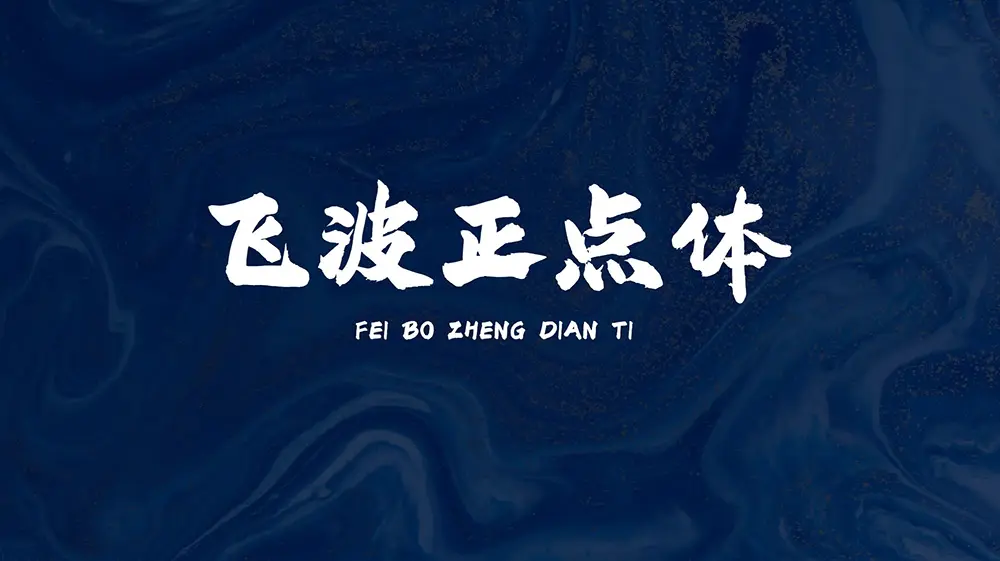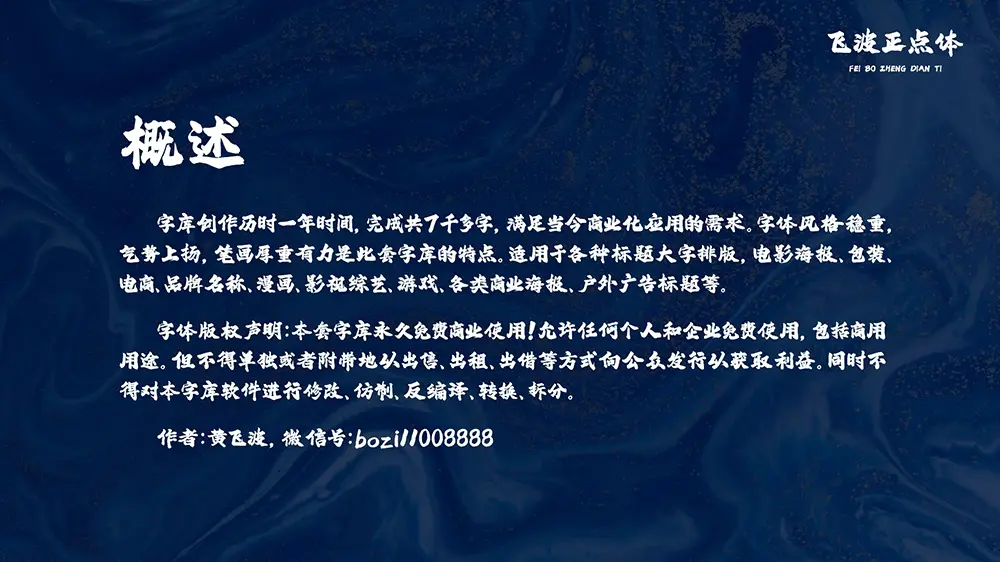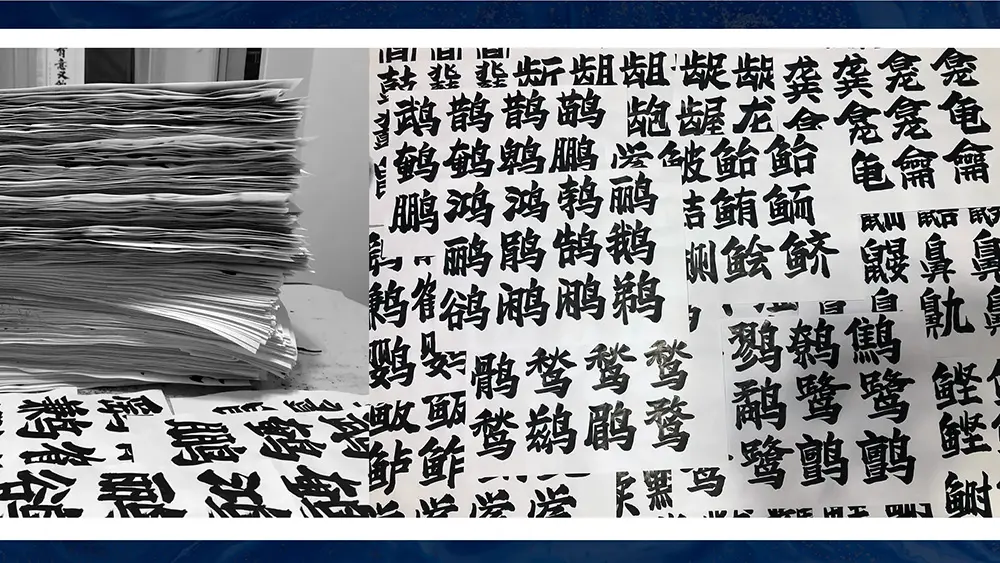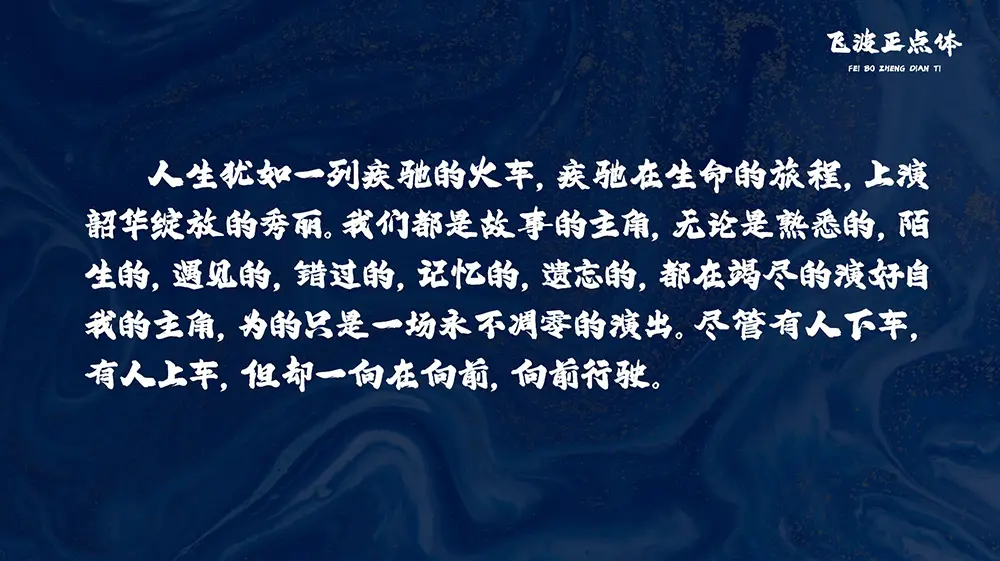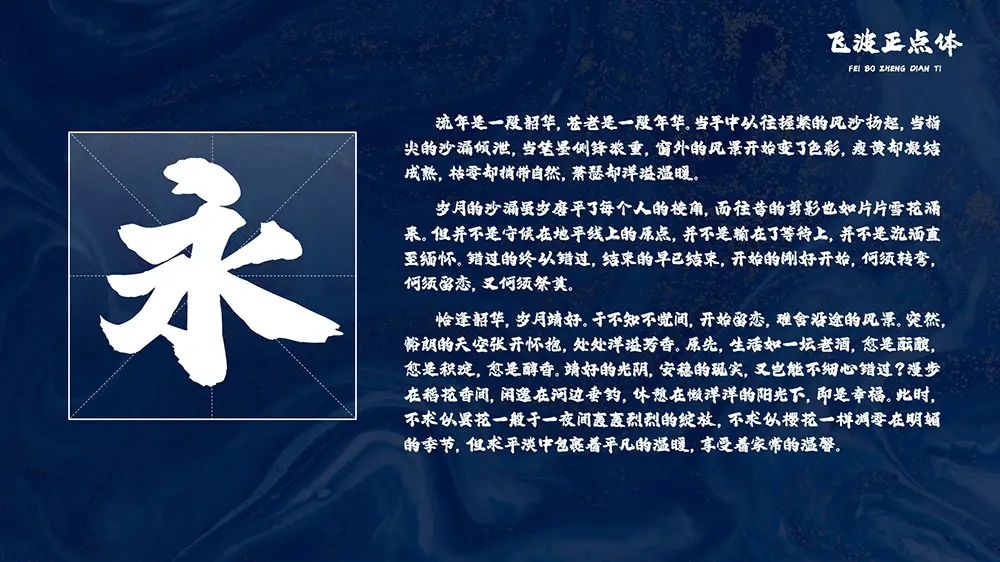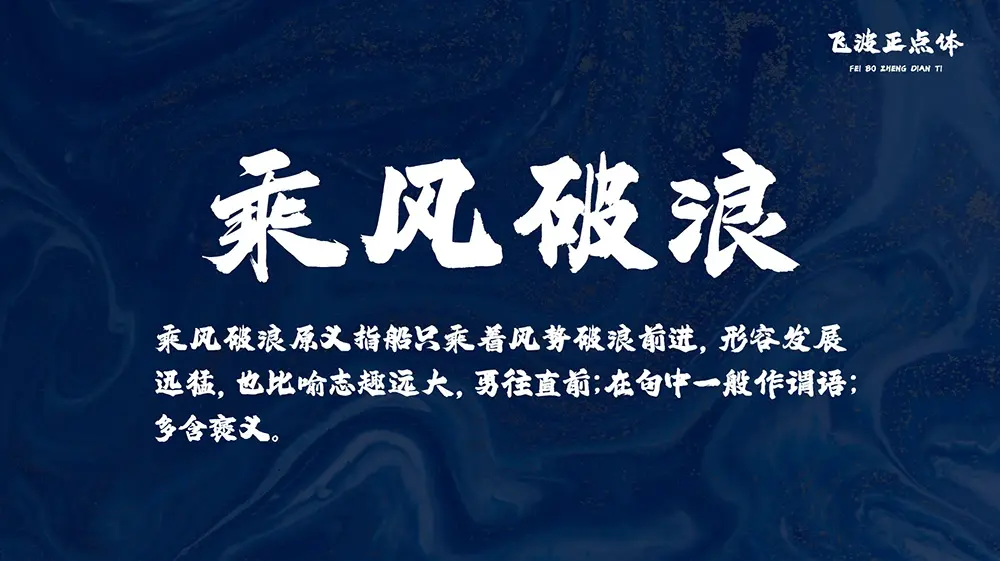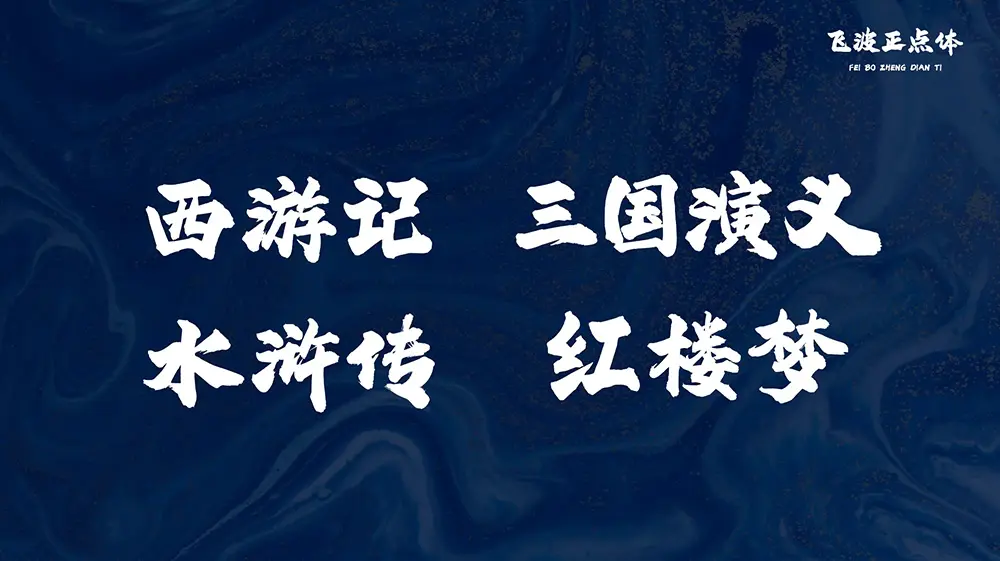
飛波正點體預覽
飛波正點體介紹
飛波正點體由本人從毛筆手寫到後期軟件封裝,創作歷時一年時間,完成共7千多字。初次製作字庫,經驗不足之處,歡迎指正。
字體風格穩重,氣勢上揚,筆畫厚重有力是此套字庫的特點。適用於各種標題大字排版,電影海報、包裝、電商、品牌名稱、漫畫、影視綜藝、遊戲、各類商業海報、戶外廣告標題等。